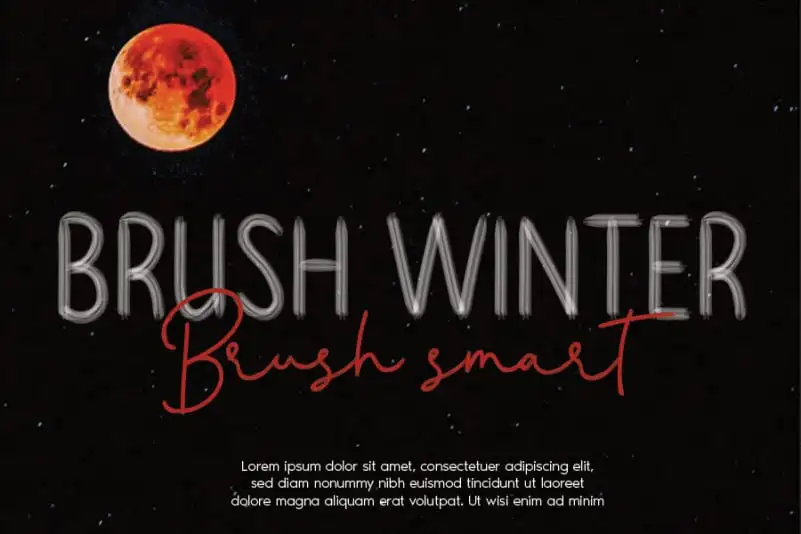
Brush Winter Script Font – Download Grátis
A Brush Winter Script Font é uma elegante tipografia feita com um pen a esfumar. Essa fonte traz vida à criação visual, adaptando-se perfeitamente para uma ampla variedade de projetos de design. Seja para criar marcas inovadores, destacar títulos chamativos ou personalizar cartões de aniversário e selinhos para eventos românticos, essa fonte é a escolha ideal. Ela também se adequa perfeitamente aos logos corporativos e identidades visuais, mantendo uma atmosfera encantadora e sofisticada. Com seu design autêntico e sua qualidade de escrita elegante, a Brush Winter Script Font é o companheiro perfeito para designers em todas as etapas do processo criativo.